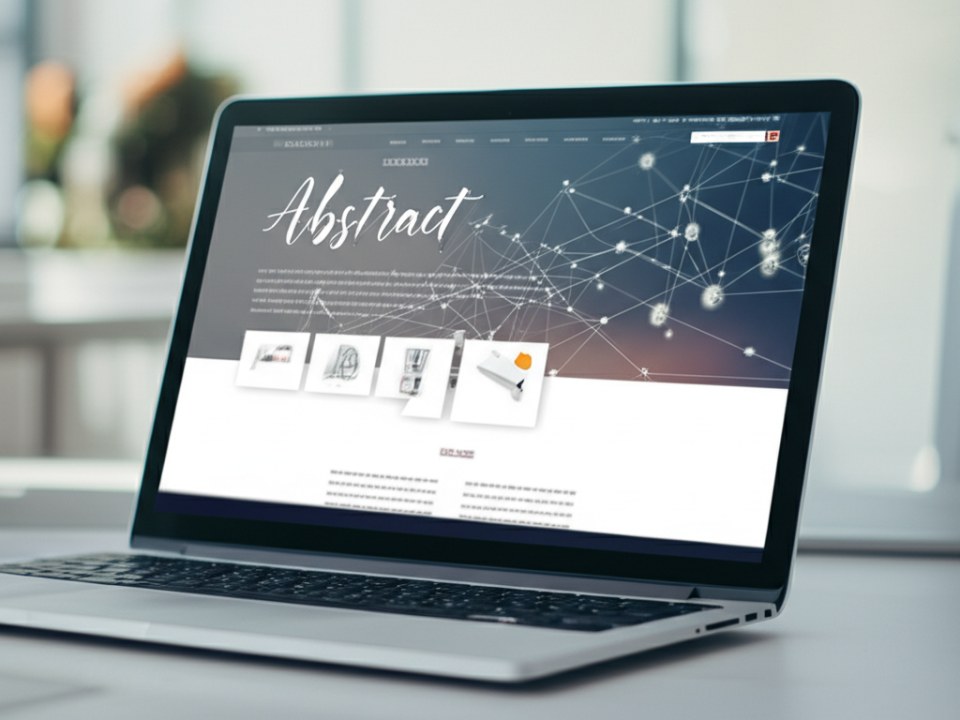
Bạn đang tìm kiếm những font chữ calligraphy việt hóa đẹp và miễn phí để thổi hồn vào thiết kế của mình? Chúng tôi đã tổng hợp sẵn bộ sưu tập hơn 50+ font chất lượng, giúp bạn tiết kiệm hàng giờ tìm kiếm và thử nghiệm.
Thực tế, việc tìm được một font chữ vừa ý, hỗ trợ đầy đủ tiếng Việt và mang phong cách thư pháp hiện đại không hề đơn giản. Nhiều font miễn phí thường gặp lỗi hiển thị dấu hoặc thiếu đi sự tinh tế cần thiết cho các dự án chuyên nghiệp, từ branding, thiệp cưới cho đến các ấn phẩm marketing.
Bài viết này không chỉ cung cấp link download font chữ calligraphy mà còn đi sâu hơn. Chúng tôi sẽ giúp bạn phân biệt rõ các phong cách từ cổ điển đến hiện đại, đồng thời hướng dẫn cách lựa chọn và phối hợp font sao cho hiệu quả nhất, đảm bảo thiết kế của bạn vừa nghệ thuật, vừa chuyên nghiệp.
Nhưng trước hết, hãy cùng làm rõ bản chất của font calligraphy và tại sao nó lại trở thành ‘gia vị’ không thể thiếu trong các thiết kế ấn tượng ngày nay.
Font chữ Calligraphy là gì và tại sao lại được ưa chuộng trong thiết kế?
Tại sao Font Calligraphy lại là ‘gia vị’ không thể thiếu trong thiết kế hiện đại?
Về cơ bản, font calligraphy là một loại typeface kỹ thuật số mô phỏng nghệ thuật viết chữ tay đẹp, với những đường nét thanh đậm uyển chuyển và nhịp điệu tinh tế. Nếu bạn đang tự hỏi font calligraphy là gì, hãy hình dung nó như linh hồn của nghệ thuật thư pháp được thổi vào thế giới số. Thay vì chỉ là công cụ truyền tải thông tin, nó còn là phương tiện để truyền tải cảm xúc, sự sang trọng và dấu ấn cá nhân.
Trong bối cảnh thiết kế đồ họa ngày càng bão hòa, việc sử dụng font calligraphy giúp một sản phẩm nổi bật tức thì. Nó mang lại “hơi ấm” và sự mềm mại, phá vỡ cảm giác khô cứng, máy móc của các font chữ thông thường. Giống như cách một bộ trang phục được may đo tỉ mỉ tôn lên vóc dáng, một font calligraphy phù hợp sẽ nâng tầm toàn bộ thiết kế của bạn, từ logo thương hiệu, thiệp cưới cho đến các ấn phẩm marketing.
Phân biệt nhanh: Calligraphy, Script và Hand-writing
Để sử dụng hiệu quả, bạn cần phân biệt rõ ba khái niệm thường bị nhầm lẫn trong typography:
- Hand-writing: Là phiên bản số hóa của chữ viết tay tự do, độc đáo của một cá nhân, thường không có sự kết nối giữa các chữ cái và mang đậm tính cách riêng. Đây cũng là một trong những phong cách phổ biến của font viết tay việt hoá.
Việc hiểu rõ sự khác biệt này chính là bước đầu tiên để bạn lựa chọn đúng “diễn viên” cho “vai diễn” trong dự án của mình, đảm bảo thông điệp được truyền tải chính xác và hiệu quả nhất.
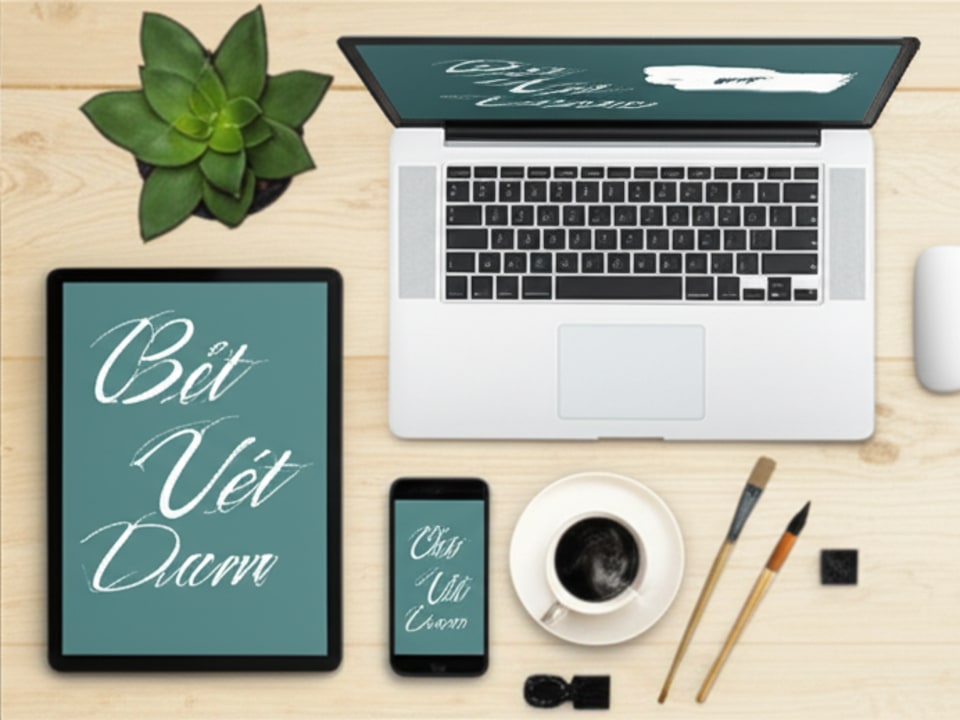
Đâu là những font Calligraphy Việt hóa đẹp và miễn phí đáng tải nhất?
Nhóm font Calligraphy hiện đại, tối giản
Với những dự án cần sự thanh lịch, tinh tế nhưng không quá cầu kỳ, các font hiện đại là lựa chọn hàng đầu.
- SVN-Allegratta: Nét chữ gọn gàng, dứt khoát nhưng vẫn giữ được độ mềm mại cần thiết. Font này là lựa chọn tuyệt vời cho các thiết kế logo, branding cho spa, thời trang hoặc các ấn phẩm tối giản.
- iCiel Beelove: Một font chữ mang cảm giác vui tươi, thân thiện, phù hợp cho các thương hiệu hướng đến giới trẻ, thiệp mời sự kiện hoặc các bài đăng mạng xã hội.
Nhóm font Calligraphy cổ điển, sang trọng
Đây là nhóm font lý tưởng để tạo ra cảm giác trang trọng, lãng mạn và đẳng cấp.
Great Vibes Việt Hóa: Được xem là một font chữ thư pháp việt hóa kinh điển, hoàn hảo cho thiệp cưới, menu nhà hàng cao cấp hay các trích dẫn nghệ thuật. Nét chữ nối liền mềm mại tạo cảm giác sang trọng vượt thời gian.
Làm thế nào để chọn Font Calligraphy phù hợp với dự án của bạn?
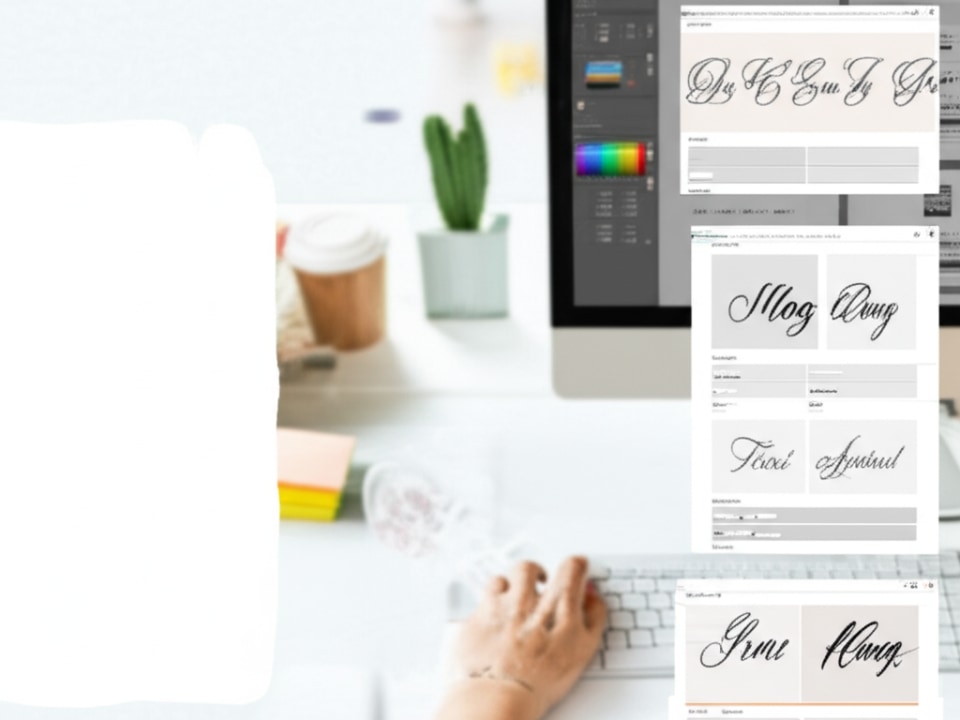
Làm sao để chọn Font Calligraphy phù hợp nhất cho dự án?
Để tìm ra cách chọn font chữ hiệu quả, bạn cần xem nó như một diễn viên: phải hợp vai và truyền tải đúng cảm xúc. Thay vì chọn theo cảm tính, hãy đánh giá font dựa trên ba tiêu chí cốt lõi: thông điệp thương hiệu, tính dễ đọc trong ngữ cảnh thực tế, và khả năng kết hợp hài hòa với các yếu tố thiết kế khác.
Font UTM và SVN khác nhau như thế nào?
UTM (Utopian Type) và SVN (Style’s Font) không phải là các loại font khác nhau mà là tiền tố được đặt bởi hai cộng đồng thiết kế đã có công Việt hóa và chia sẻ chúng. Sự khác biệt không nằm ở bản chất kỹ thuật mà ở nguồn gốc. Cả hai đều cung cấp nhiều font chất lượng, vì vậy thay vì chỉ tập trung vào tiền tố, bạn nên đánh giá từng font cụ thể dựa trên thiết kế, độ hoàn thiện của bộ dấu và giấy phép sử dụng.